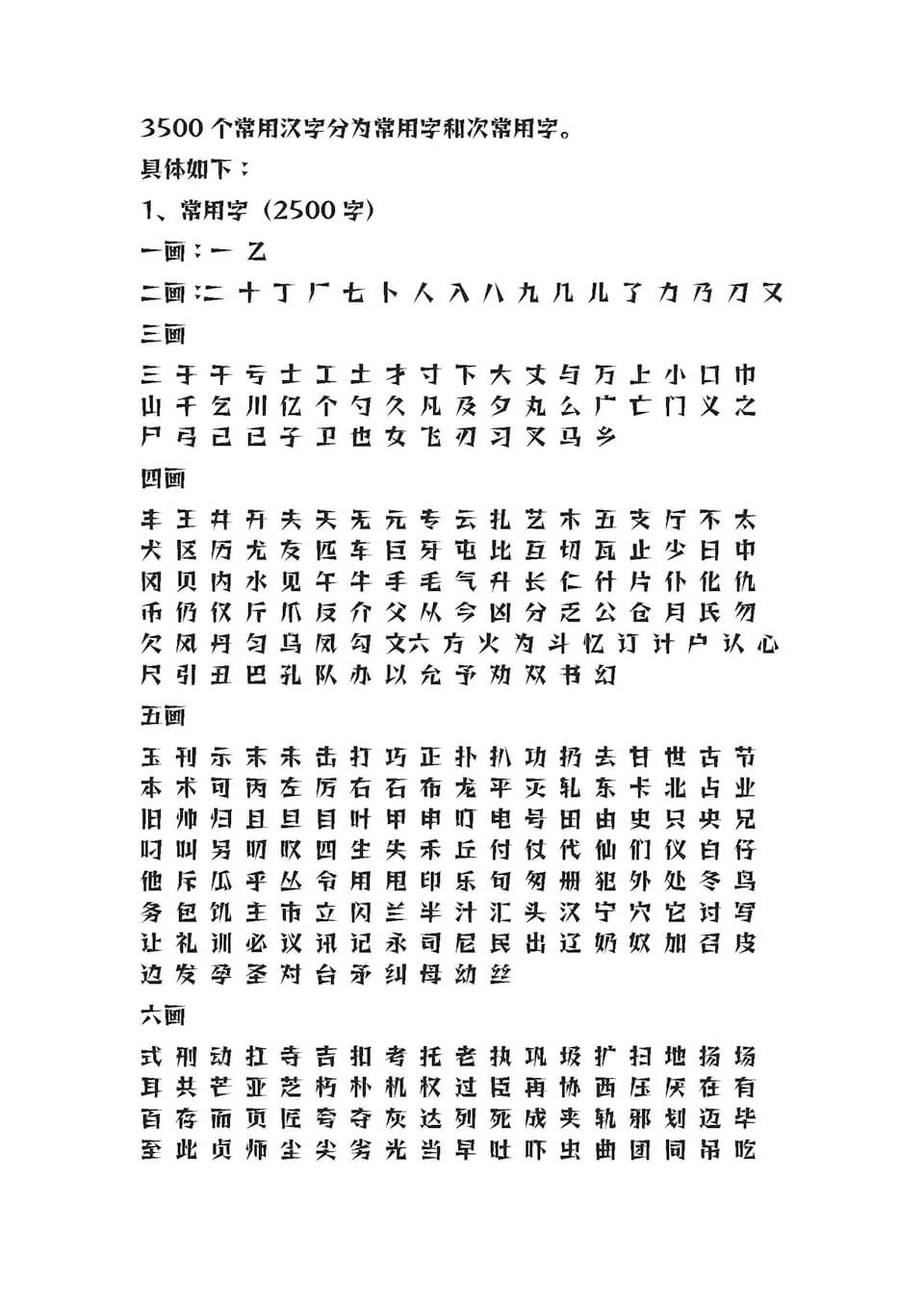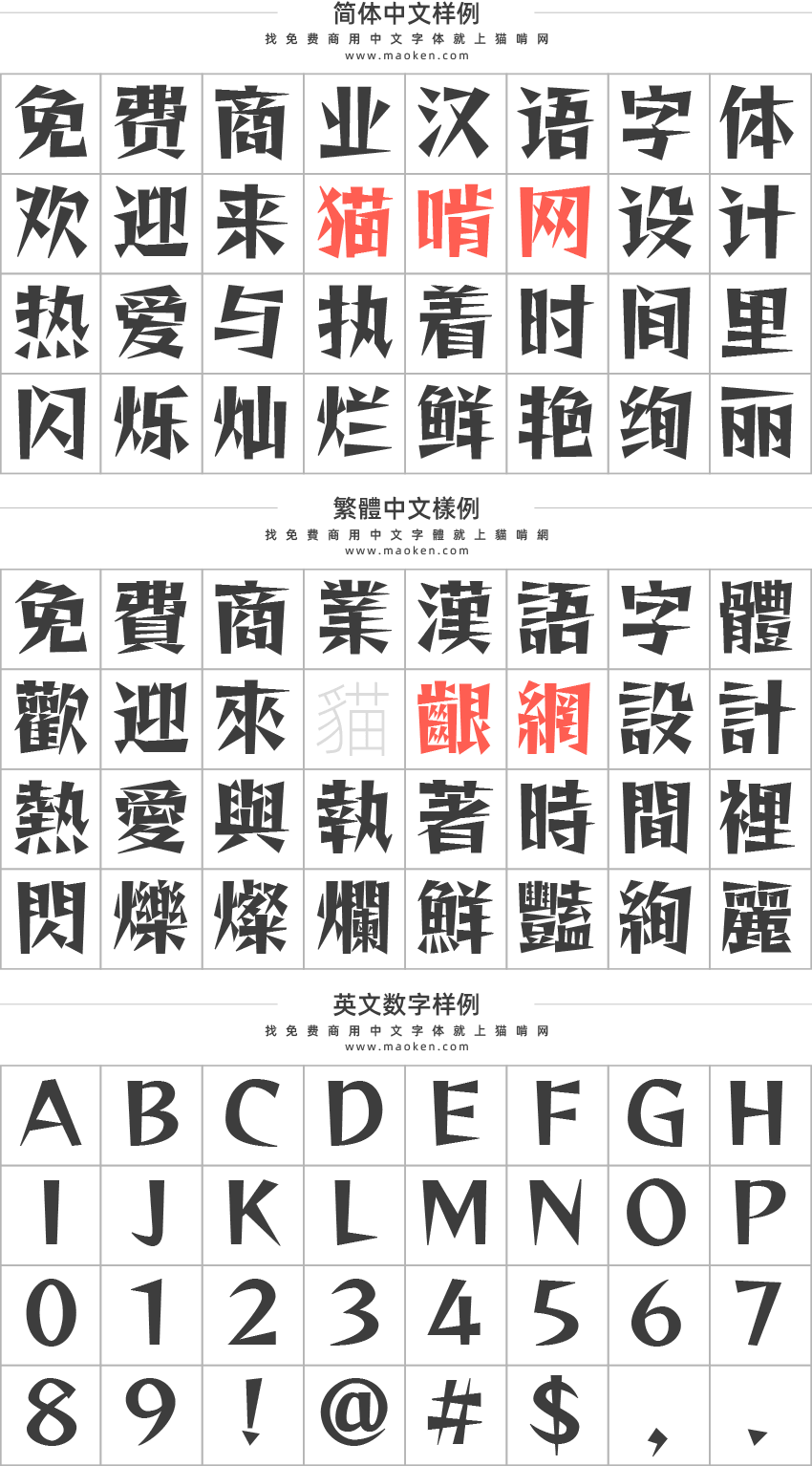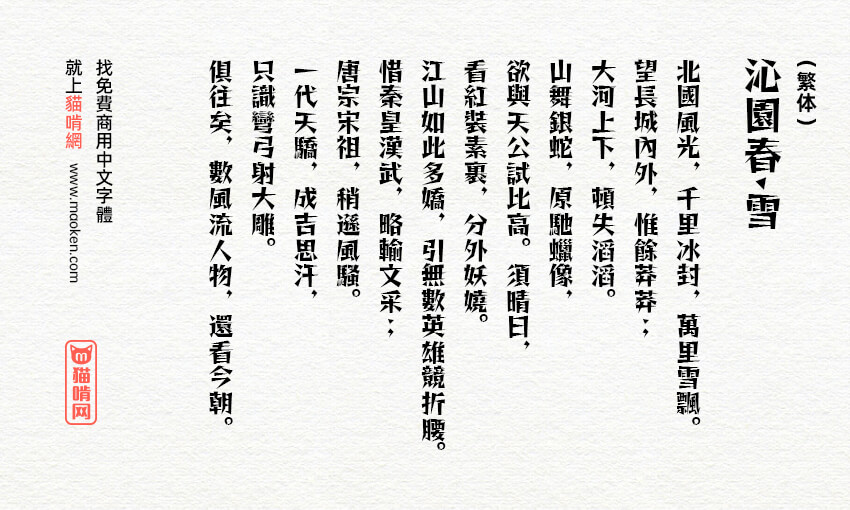
雷盖体:猫啃新人基于雷鬼One补全缺失简体字体 免费商用
字体作者:猫啃新人 (中国大陆) 字体字重:1个
“雷盖体”是根据日本著名字体设计公司Fontworks免费开源的一款字体“日文名:レゲエ,英文名:Reggae”修改,取音译“雷盖”命名而成。字体主要以补全缺失的简体汉字和部分繁体字为主,同时视情况将部分字改为国标字形标准,部分字保留原字体风格不做修改。
现在在猫啃网首发雷盖体2.0完整版,可输出GB2312-80国家标准字符集6763个汉字和部分繁体字。相比此前的1.0试用版进行了优化和调整,并更正错误字形,另外还加入部分OpenType个性化输出功能,因此请各位下载新完整版使用。
Ver 2.0(2021/12/15)
• 雷盖体完整版发布。
• 更正错误字形
• 加入部分OpenType个性化输出功能
Ver 1.01(2021/10/20)
• 优化部分字形
• 新增补约350个简体字和部分繁体字。
Ver 1.0(2021/10/12)
• 雷盖体第一版正式发布。